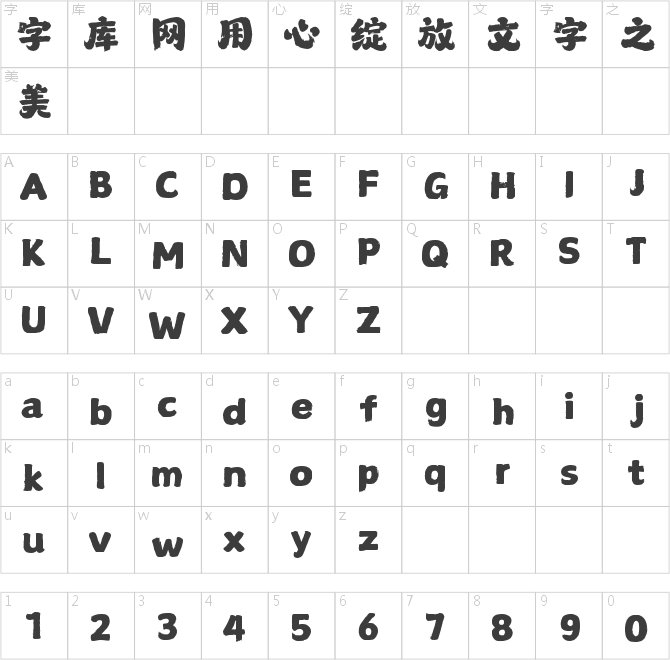
山海鸿墨手书W 详情页
字体名称: 山海鸿墨手书W
山海鸿墨手书W
山海鸿墨手书W介绍
山海鸿墨手书,是一款毛笔字体,包含简繁汉字9169个。这款字体书写笔锋厚重,同时用笔轻松随性,整体给人一种放松柔美的视觉效果。笔画的飞白效果使字体的气息更加流畅,笔画间的关系密不可分,同时也增加了字体的自由洒脱之感。